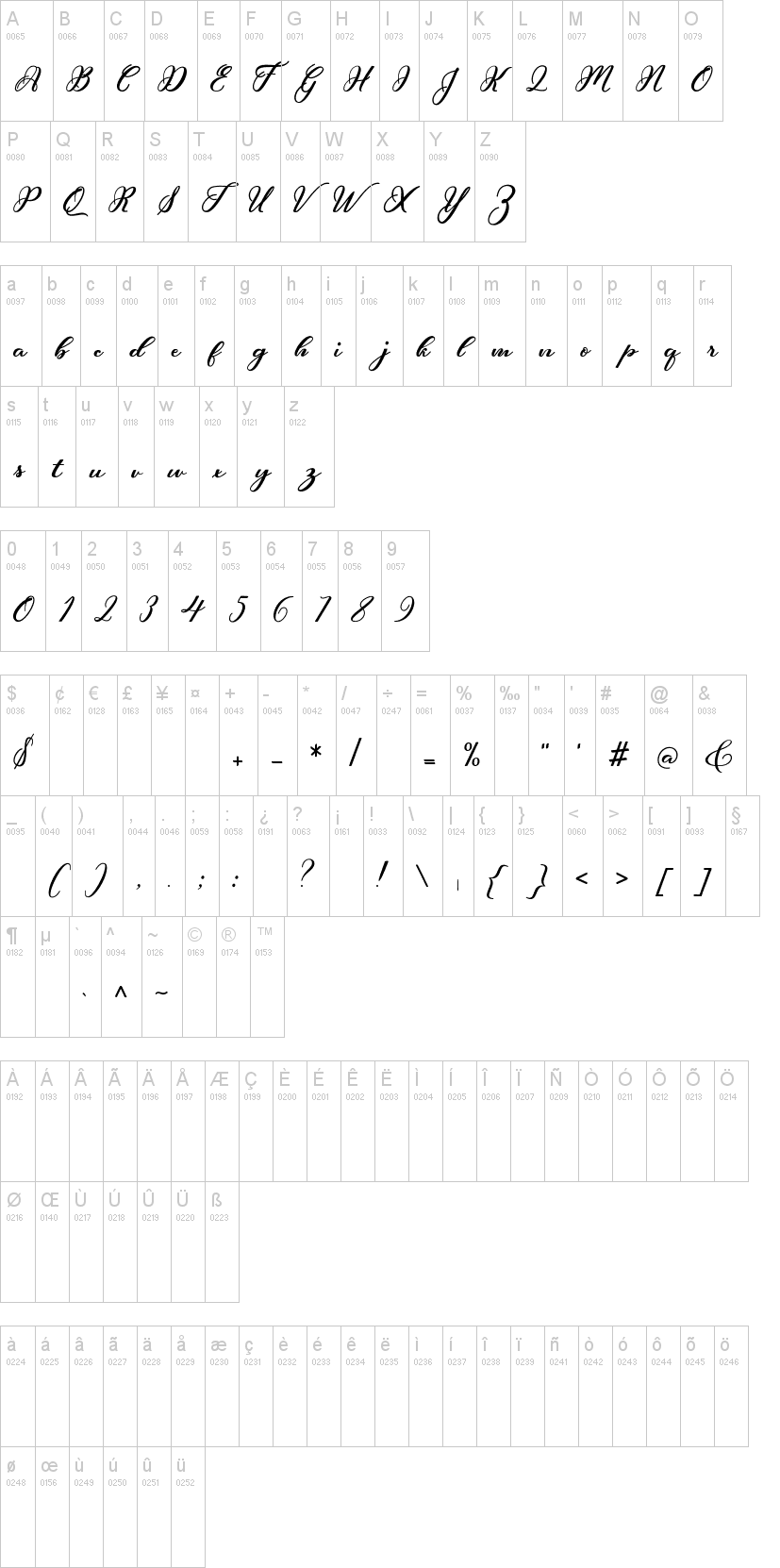
Hunkydory
? Hunkydory 字体是一款设计师字体,由著名设计师 Paul Lloyd 创作。它是一款时尚、可爱的英文字体,采用曲线与角度的结合,充满动感,可以在任何文字和绘图项目中使用。它的字体特点是清晰、简洁,可以在网页、印刷、广告、标志、标识和其他设计项目中使用。
Hunkydory是一款非常不错的手写艺术字体,具有很好的视觉感,适合于文化类的宣传设计、商业类品牌的广告和产品包装设计以及个性化文字排版等较多场景。